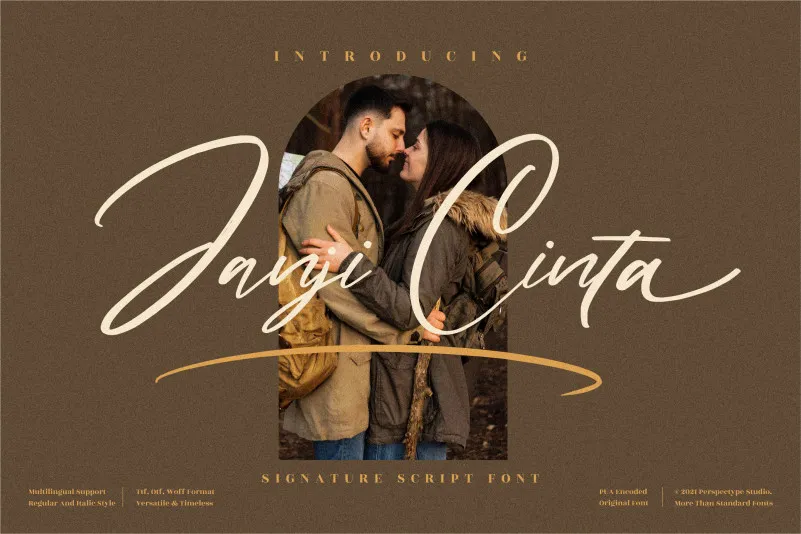
Janji Cinta Font – Download Grátis
A fonte ‘Janji Cinta’ é uma escolha perfeita para quem busca um touch personalizado para suas criações digitais. Essa elegante fonte escrita a mão traz uma experiência única, genuína e com movimentos fluidos que podem dar um toque especial a qualquer trabalho artístico — desde cartões de aniversário delicadamente decorados até selinhos para eventos formais, ou mesmo logos profissionais. Seja qual seja o seu projeto, essa fonte é versátil demais para ignorar. Sem dúvida uma adição incrível ao seu arsenal criativo.